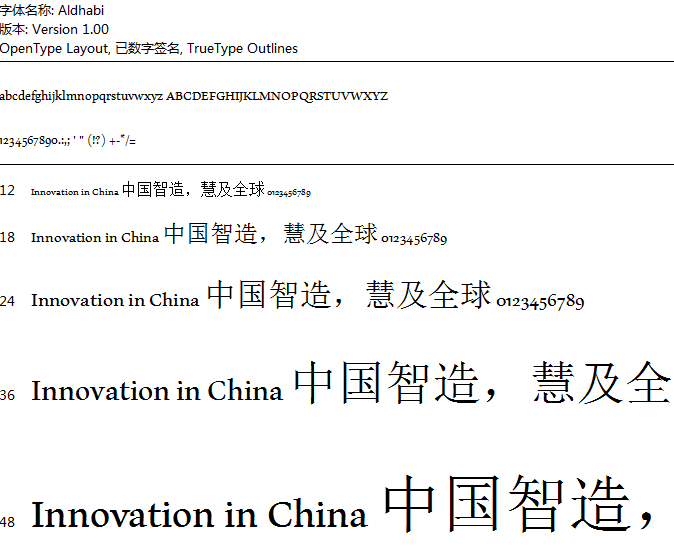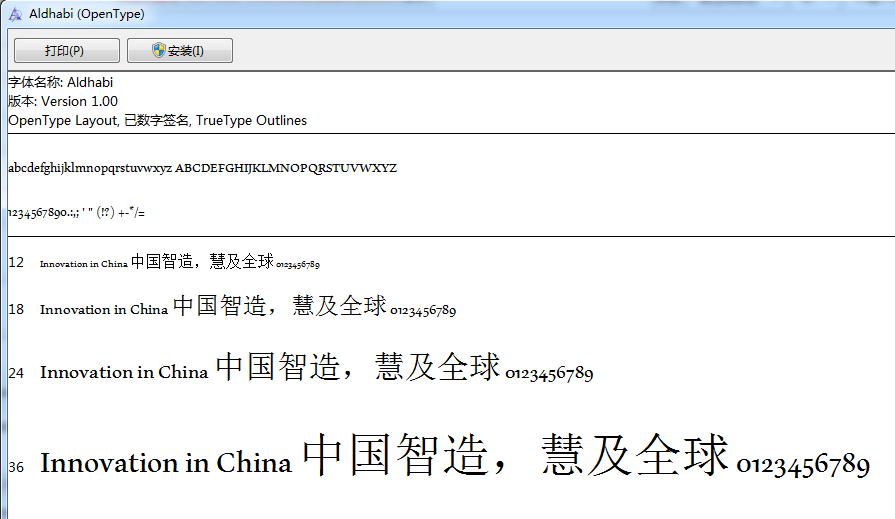
aldhabi font free是專為電腦系統(tǒng)打造的字體安裝包,這款字體講究橫平豎直,看起來(lái)方方正正比較嚴(yán)肅,可以支持windows7、win8等不同的系統(tǒng),安裝步驟也相當(dāng)簡(jiǎn)單,多種方法供大家選擇,需要的話歡迎前來(lái)下載使用!